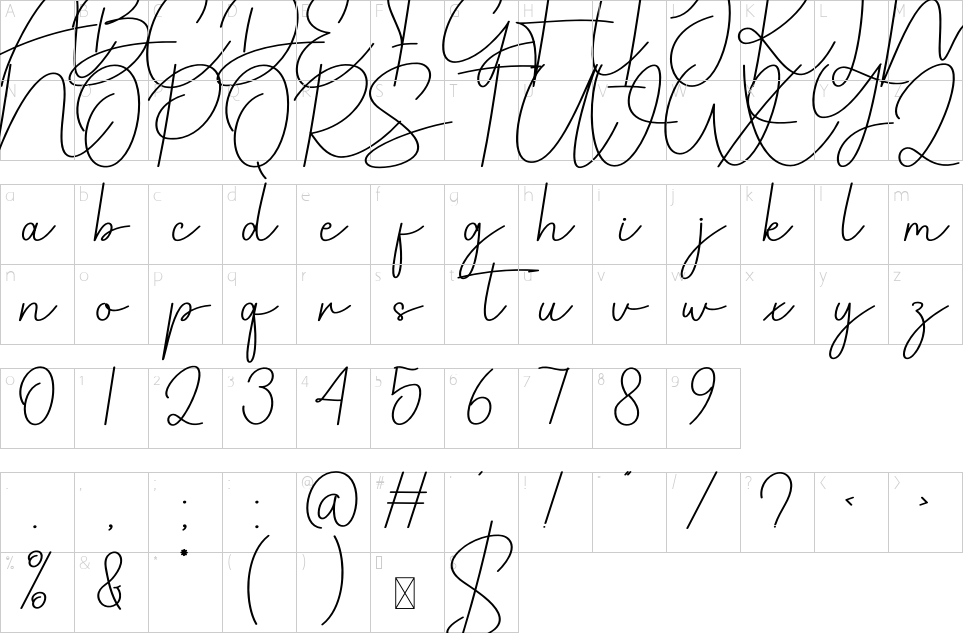
A American Signature é uma elegante e sofisticada fonte criada por scratchones, disponível tanto para sistemas Windows quanto para Mac. Esta fonte, com seus elegantes traços retos e linhas arredondadas, é perfeita para gráficos e projetos de escritório. Seu design clean e moderno faz dela uma opção versátil para anúncios, sites, logotipos e muito mais. Desde que foi lançada, a American Signature tem sido um download popular, mostrando a qualidade e simplicidade que a font oferece. Para designers que procuram uma fonte moderna e profissional, a American Signature é uma escolha ótima.